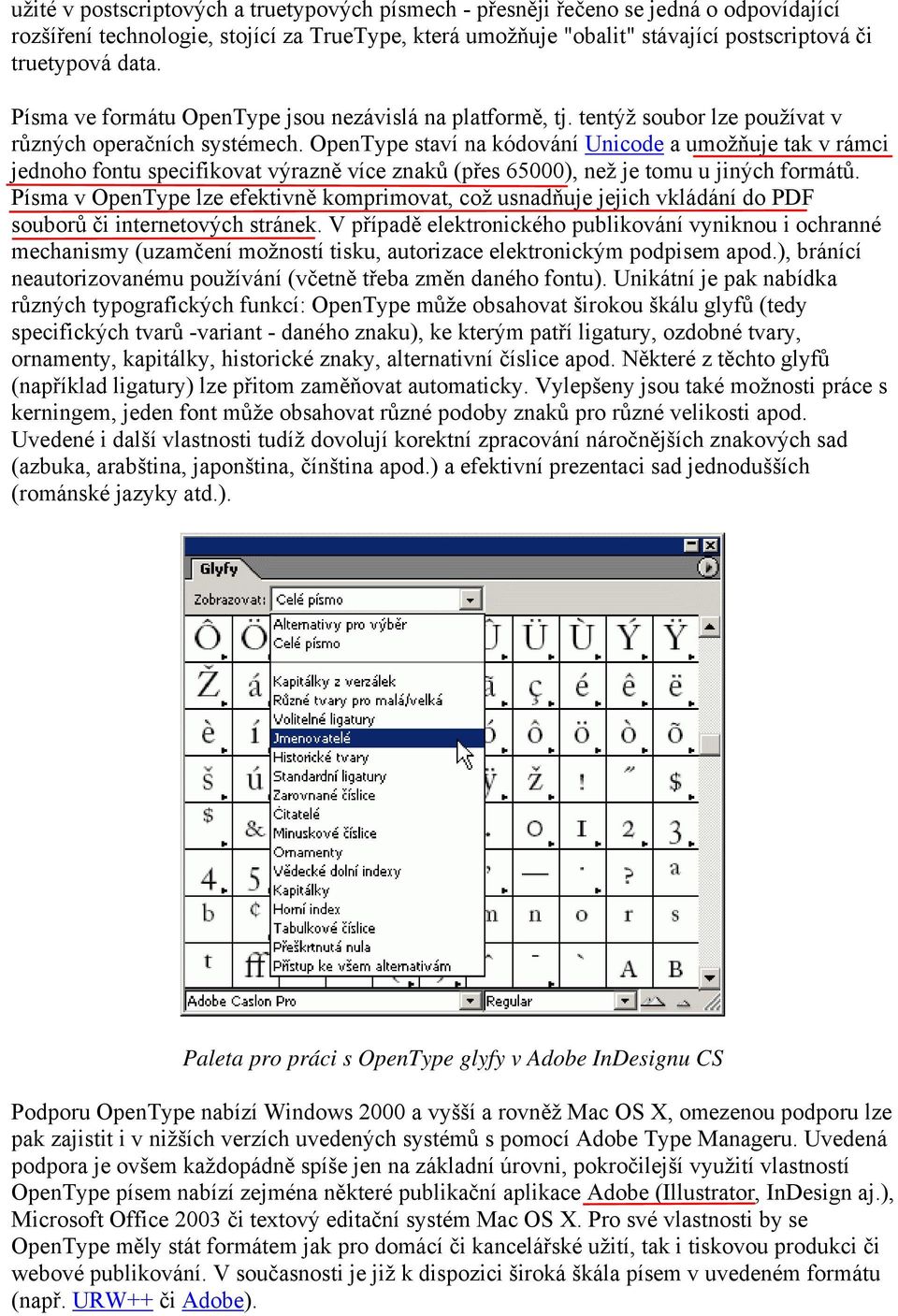
1 Encyklopedie publikačních formátů: Počítačová písma Autor: Krejčí Richard - Typ: Článek Type 1, TrueType, OpenType: všichni uživatelé dnes přinejmenším s některými z uvedených standardů pro počítačovou reprezentaci písma pracují. Kolik je toho ale o uvedených formátech všeobecně známo? V tomto díle naši encyklopedie přinášíme základní informace, umožňující se ve světě počítačových písem lépe orientovat. Rubrika: Sazba Technologie pro počítačová písma jsou nezbytnou základní výbavou každého počítačového systému. A co víc, jejich použití je naprosto zásadní při tvorbě publikací, ať už se jedná o podklady pro tiskový výstup či elektronické publikování. S postupem času se prosadilo několik písmových technologií, které dnes i v oblasti publikačního průmyslu resp. jeho aplikací vedle sebe různým způsobem koexistují. V tomto našem článku bychom se rádi pokusili o jejich přiblížení. Vzhledem k rozsáhlosti dané problematiky se přitom pokusíme zaměřit zejména na údaje týkající se globálních vlastností daných technologií, podrobnosti, spojené s užíváním toho či onoho písmového formátu, pak lze dohledat pod odkazy, umístěnými v článku. Postscriptová písma Jednou z nejstarších písmových technologií, používanou stále v dnešním publikačním průmyslu, jsou postscriptová písma. (Ještě starší je například rovněž stále používané bitmapové písmo TeXu.) Od poloviny 80. let minulého století jsou k dispozici v rámci jazyka PostScript, vytvořeného a spravovaného společností Adobe. Již první verze PostScriptu (Level 1), přitom poskytla základní formát postscriptového písma Type 1, který se bez větších změn používá dodnes zejména v pre-pressu. (Vedle něj je k dispozici například i méně kvalitní formát Type 3 a pro speciální účely - viz dále - určený Type 42. Adobe rovněž v průběhu let vyvinula v rámci PostScriptu tzv. kompozitní /CID/ fonty, určené zejména pro reprezentaci asijských znakových sad a technologii Multiple Master /různorodé změny typografických parametrů/, kterou ovšem posléze přestala vyvíjet a dnes využívá pouze v některých aplikacích.)
2 Ukázka postscriptového písma Obdobně jako ostatní hlavní písmové technologie jsou postscriptová písma založená na vektorovém popisu. To znamená, že je lze při použití vhodného softwarového vybavení bez ztráty kvality prakticky libovolným způsobem transformovat (zvětšovat, naklánět atp.) a zobrazovat na nejrůznějších výstupních zařízeních. Z technického hlediska je Type 1 font vlastně postscriptovým programem, který pro své vykreslení vyžaduje příslušný interpret resp. rastrovací program. Tím je v případě tiskáren, osvitových jednotek či jiných obdobných výstupních zařízení postscriptový RIP, na obrazovce či nepostscriptových zařízeních se o vykreslení písem starají buďto zabudované služby systému (Windows od verze 2000, Mac OS X, X Window System v Linuxu či Unixu) nebo speciální utilita Adobe, označovaná jako Adobe Type Manager, kterou si lze v Lite podobě stáhnout a používat zdarma. Pro zobrazení písma na obrazovce či nepostscriptovém zařízení se používá bitmapových podob daného písma (tzv. screen font) generovaných v různých velikostech a řezech, pro výstup přes postscriptový RIP se pak používá soubor s vektorovým popisem (tzv. printer font). Postscriptová písma jsou závislá na platformě, to znamená, že je nelze bez konverze odpovídajícími utilitami používat na jiném operačním systému, než pro který jsou určena. Dokáží také reprodukovat jen omezený počet znaků (256 u Type 1), a proto je třeba pro jejich užití volit vždy správnou verzi kódování, odpovídající danému jazykovému prostředí. Nebývají obvykle součástí dodávky operačních systémů, takže je uživatel musí získat z jiných zdrojů (nákupem či volným stažením z Internetu apod.). Původně si Adobe držela v podstatě monopol na používání Type 1 písem (resp. vyžadovala neúměrné licenční poplatky), ten však postupně zmizel, s ním pak přibyla velmi pestrá nabídka kvalitních a zajímavých postscriptových písem, která ovšem nemohou překonat základní technická omezení dané technologie, kvůli kterým se zřejmě do popředí dostanou jiné formáty.
3 Adobe Type Manager TrueType Skutečnost, že Adobe měla v počátku neúnosné nároky na licenční poplatky za užívání Type 1 písem, vedla společnosti Apple a Microsoft k tomu, aby vyvinuly konkurenční technologii TrueType. Základní sada písem v tomto formátu se pak stala součástí instalace dnešních operačních systémů. Pro zobrazení TrueType a jejich výstup na nepostscriptových tiskárnách není třeba žádného speciálního prostředku, všechny operace jsou zajišťovány přímo systémem. I truetypová písma jsou závislá na platformě a kódování. Teoreticky jsou TrueType stejně kvalitní jako písma postscriptová, mnohdy se ovšem setkáme s písmy v tomto formátu, které nebyly připraveny příliš pečlivě. Navíc mohou vznikat problémy při výstupu na postscriptových zařízeních, i když poměrně uspokojivé řešení uvedeného problému přinesla technologie Adobe Type 42, která, zjednodušeně řečeno, zařídí "obalení" truetypového písma postscriptovým kódem před jeho odesláním do výstupního zařízení. (Podporováno až od určité verze PostScriptu Level 2.) Z těchto i dalších důvodů jsou v pre-pressu a obecně všude tam, kde je vyžadován vysoce kvalitní výstup, spíše preferována písma postscriptová ve formátu Type 1 nebo písma OpenType. Na druhou stranu se s truetypovými písmy výrazně počítá při běžném domácím a kancelářském zpracování dokumentů a také při internetovém či jiném elektronickém publikování. OpenType Výše naznačené problémy s počítačovými písmy se snaží překlenout technologie OpenType, vzešlá ze spolupráce společností Adobe a Microsoft (specifikace publikována v roce 1997, první písma zveřejněna v roce 2000). OpenType spojuje dohromady technologické principy
4 užité v postscriptových a truetypových písmech - přesněji řečeno se jedná o odpovídající rozšíření technologie, stojící za TrueType, která umožňuje "obalit" stávající postscriptová či truetypová data. Písma ve formátu OpenType jsou nezávislá na platformě, tj. tentýž soubor lze používat v různých operačních systémech. OpenType staví na kódování Unicode a umožňuje tak v rámci jednoho fontu specifikovat výrazně více znaků (přes 65000), než je tomu u jiných formátů. Písma v OpenType lze efektivně komprimovat, což usnadňuje jejich vkládání do PDF souborů či internetových stránek. V případě elektronického publikování vyniknou i ochranné mechanismy (uzamčení možností tisku, autorizace elektronickým podpisem apod.), bránící neautorizovanému používání (včetně třeba změn daného fontu). Unikátní je pak nabídka různých typografických funkcí: OpenType může obsahovat širokou škálu glyfů (tedy specifických tvarů -variant - daného znaku), ke kterým patří ligatury, ozdobné tvary, ornamenty, kapitálky, historické znaky, alternativní číslice apod. Některé z těchto glyfů (například ligatury) lze přitom zaměňovat automaticky. Vylepšeny jsou také možnosti práce s kerningem, jeden font může obsahovat různé podoby znaků pro různé velikosti apod. Uvedené i další vlastnosti tudíž dovolují korektní zpracování náročnějších znakových sad (azbuka, arabština, japonština, čínština apod.) a efektivní prezentaci sad jednodušších (románské jazyky atd.). Paleta pro práci s OpenType glyfy v Adobe InDesignu CS Podporu OpenType nabízí Windows 2000 a vyšší a rovněž Mac OS X, omezenou podporu lze pak zajistit i v nižších verzích uvedených systémů s pomocí Adobe Type Manageru. Uvedená podpora je ovšem každopádně spíše jen na základní úrovni, pokročilejší využití vlastností OpenType písem nabízí zejména některé publikační aplikace Adobe (Illustrator, InDesign aj.), Microsoft Office 2003 či textový editační systém Mac OS X. Pro své vlastnosti by se OpenType měly stát formátem jak pro domácí či kancelářské užití, tak i tiskovou produkci či webové publikování. V současnosti je již k dispozici široká škála písem v uvedeném formátu (např. URW++ či Adobe).
5 Závěrem I když je technologie OpenType jednoznačně nejzajímavější, nezdá se, že by zatím výrazněji ohrožovala stávající pozici konkurenčních písmových technologií. Problémem zde je jednak pozvolná výroba odpovídajících písem a nástrojů a dále samozřejmě konzervativnost uživatelů, kteří neradi investují čas a finance do nových, byť lákavě vyhlížejících prostředků, když ty stávající jim slouží dostatečně dobře.